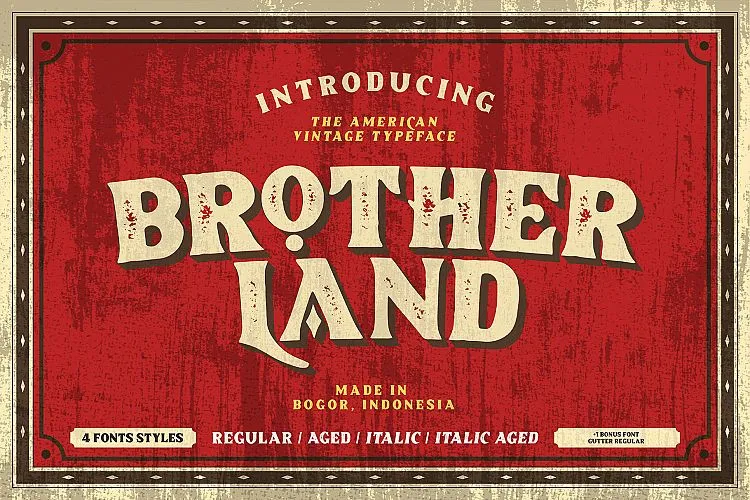
Brotherland American Vintage Font – Download Grátis
Essa é uma fonte vintage desenvolvida para cartões de etiquetas, criada com o intuito de se adaptar ao estilo moderno. Uma tipografia masculina e vintage perfeita para estilos gráficos e logos. Essa fonte nostálgica funciona super bem tanto em logomarcas quanto na criação de qualquer tipo de design vintage ou para outros trabalhos relacionados. Introduzimos a fonte Brotherland, um tipo serif feito à mão inspirado nos americanos vintage typography. Brotherland inclui quatro estilos básicos: regular, itálico, velho e velho itálico. É perfeitamente adequada tanto para logomarcas quanto para elementos de identificação visual como as etiquetas ou materiais em geral. Esta fonte atende a qualquer necessidade que tenha algo vintage para oferecer. Suas linhas fortes e características vintage realmente destacam suas qualidades, tornando-a uma opção perfeita para qualquer designer buscando um toque de nostalgia em seus projetos.